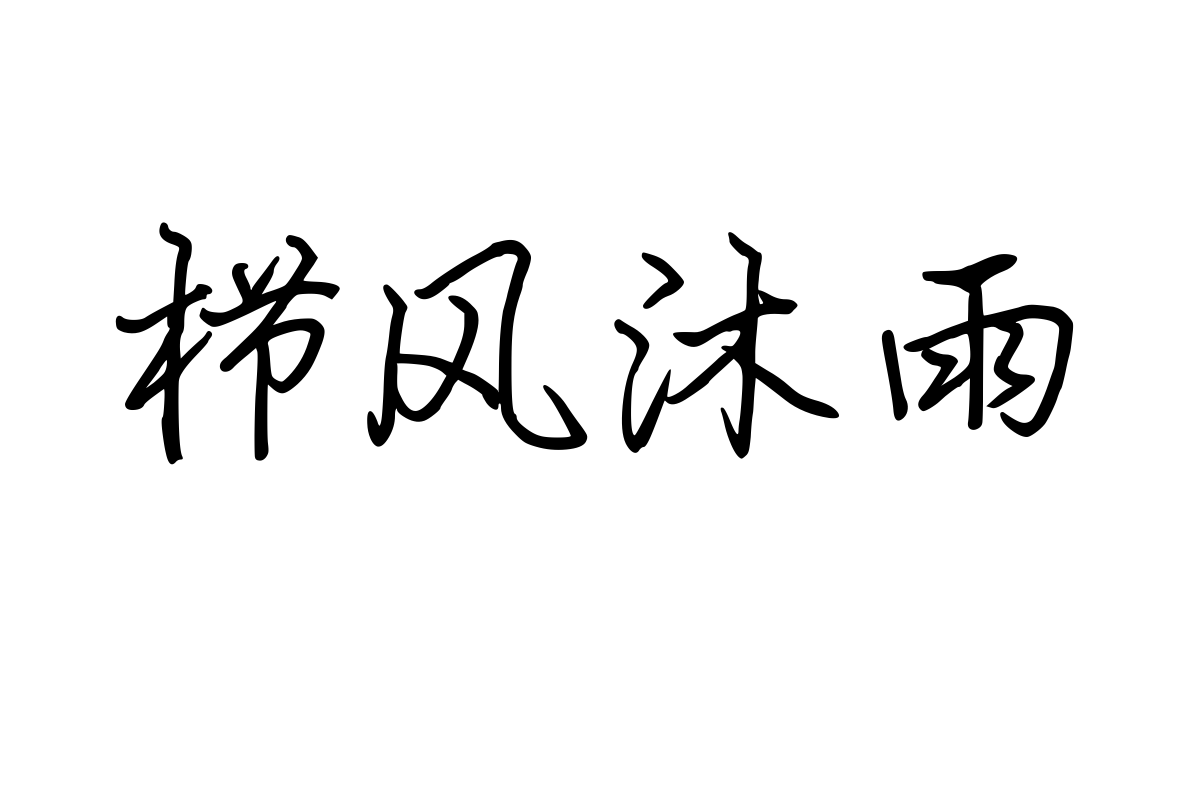
蝉羽刀剑柔情是一种具有独特美感和艺术风格的字体。它采用了流畅的线条和柔和的笔画,给人一种轻盈、优雅的感觉。这种字体特别适合用于需要表达柔美、细腻情感的场合,如诗歌、歌词、散文等。
蝉羽刀剑柔情的字体特点如下:
1. 线条流畅:该字体的笔画线条流畅自然,没有生硬的折角,给人一种舒适的感觉。
2. 柔和圆润:字体中的每个字都呈现出柔和的弧度,使得整体看起来更加和谐。
3. 简洁大方:虽然线条流畅,但整体字形并不复杂,简洁大方,易于阅读和识别。
4. 适合多种场景:无论是用于印刷品还是电子媒体,蝉羽刀剑柔情都能很好地融入其中,展现出独特的艺术魅力。
总之,蝉羽刀剑柔情是一种非常独特且具有艺术感的字体,非常适合用于需要表达柔美、细腻情感的场合。
蝉羽刀剑柔情